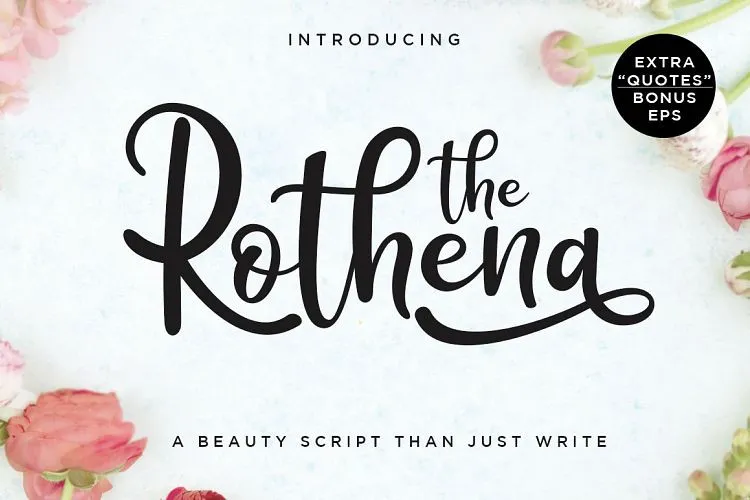
The Rothena Script Font – Download Grátis
A Rothena Script é uma elegante fonte tipográfica que vai dar um toque especial a seu próximo projeto. Este design foi criado para além do simples uso de escrita, e pode ser entendido como uma coleção única de tinta contínua com movimento natural. A Rothena Script é perfeitamente adequada para projetos de design em geral, e é especialmente útil para elementos gráficos como cartões de aniversário, identidade de marca, papelaria, redes sociais, embalagens, layouts de revistas e impressão. É a fonte certa para dar vida ao seu trabalho, tornando-o mais sofisticado e atraente. Uma vez que você adquire esta fonte, vai se lembrar do conforto e da elegância que ela traz para seus projetos. Essa fonte é perfeita para quem procura algo que ofereça uma sensação de luxo e sofisticação. Ela pode ser usada em diferentes formatos de projeto, desde simples cartões de aniversário até layouts de revistas profissionais, garantindo sempre um toque elegante e único. Com a Rothena Script, você terá todas as ferramentas necessárias para personalizar sua marca e capturar o olhar do seu público-alvo. Aproveite essa oportunidade para adicionar uma paleta de textura e expressão à sua identidade visual!